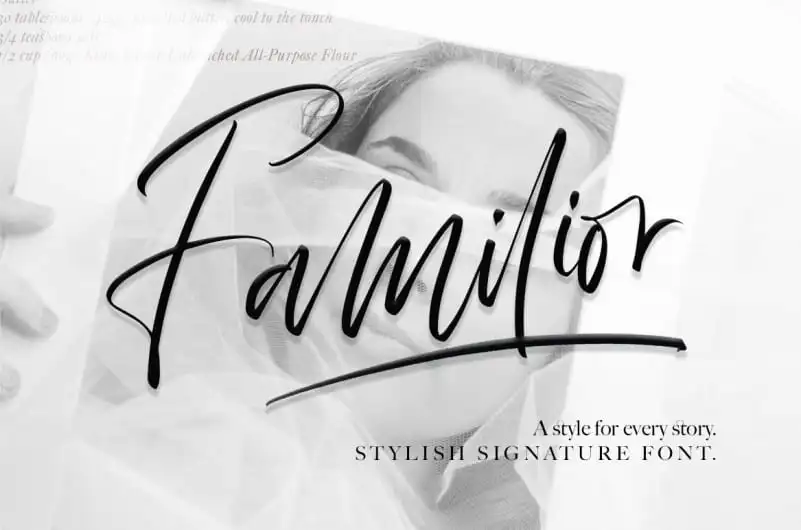
Familior Signature Font – Download Grátis
A Familiar Signature é uma fonte familiarizada com traços escrita a mão que traz alternativas e ligaturas naturais para criar um texto encantador e expressivo, mas sempre levemente funcional. Especialmente adaptada aos logos de assinatura, sua aparência suave e quase fluida contrasta perfeitamente entre o detalhe requintado dos logotipos de assinatura e a legibilidade necessária para qualquer fonte em grande escala ou impressão. A Familiar Signature foi criada pelo designer agniardi, uma família com alternativas que oferecem um desfecho mais expressivo, sem perder a precisão necessária para uso nos logos. Suas linhas são fluidas e quase dançantes, mas sempre respeitando o ritmo de leitura natural. Perfeito tanto para aplicar em logotipos exclusivos quanto em materiais publicitários e identidades corporativas onde se deseja transmitir um estilo elegante. Uma das características mais distintivas da fonte são suas ligaturas naturais, que permitem uma escrita fluída sem a necessidade de ajustes adicionais. O uso de alternativas também oferece um toque personalizado ao texto e pode ser usado para criar um efeito chamativo em nomes ou mensagens específicas. Por fim, não podemos esquecer da sua ligatura natural que adiciona um toque final de expressividade e encanto à Familiar Signature, tornando-a uma opção ideal tanto para aplicativos digitais quanto para impressão.